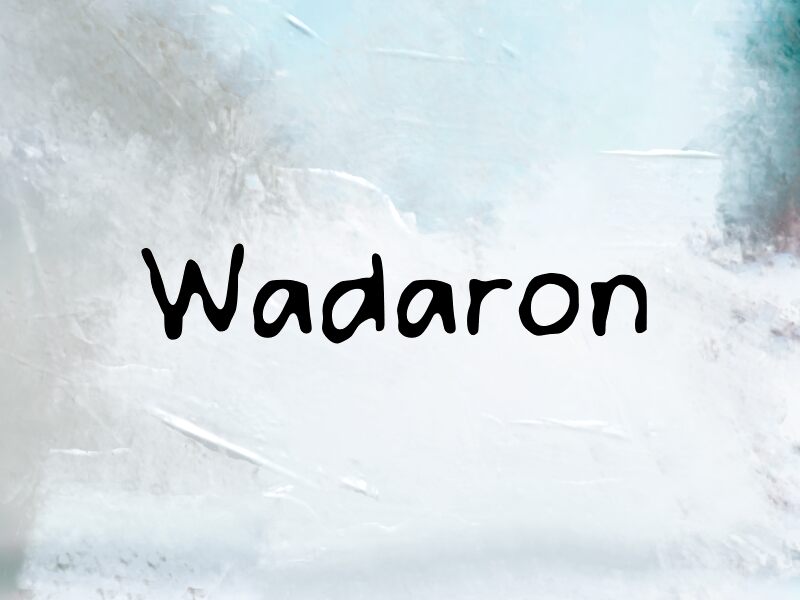
Wadaron par Wep est une police de type brush gratuite au style libre et peint à la main. Les lettres ont un aspect humide et arrondi, avec des traits épais qui s'élargissent et se resserrent de manière irrégulière, conférant à l'ensemble un rythme décontracté qui rappelle davantage le marqueur et l'encre qu'une écriture sophistiquée.
Elle est idéale pour les affiches, l'image de marque de cafés, le packaging, les visuels musicaux et les bannières de réseaux sociaux où vous recherchez un style informel mais percutant. En tant que police gratuite, Wadaron est également un excellent choix pour des cartons de titres rapides, des ébauches de logos ou de grandes citations, car ses formes douces et charnues imposent du caractère sans avoir besoin d'ornements superflus.
Wadaron
Présentation et spécimen de la police Wadaron